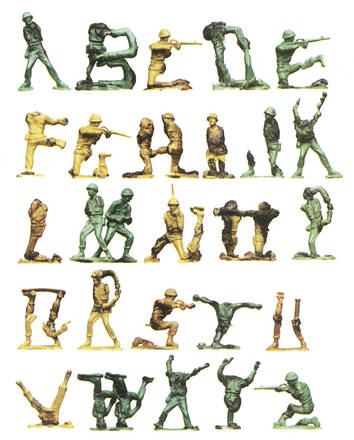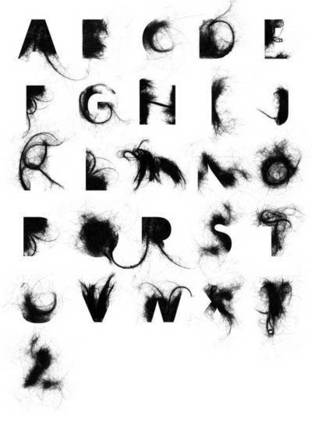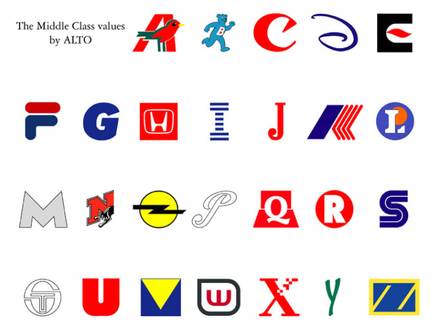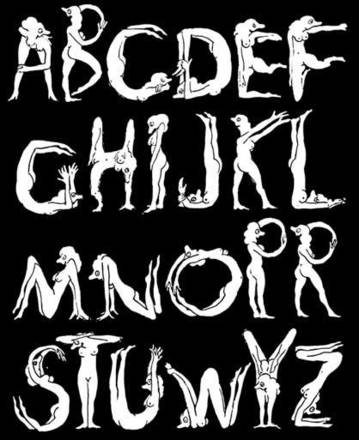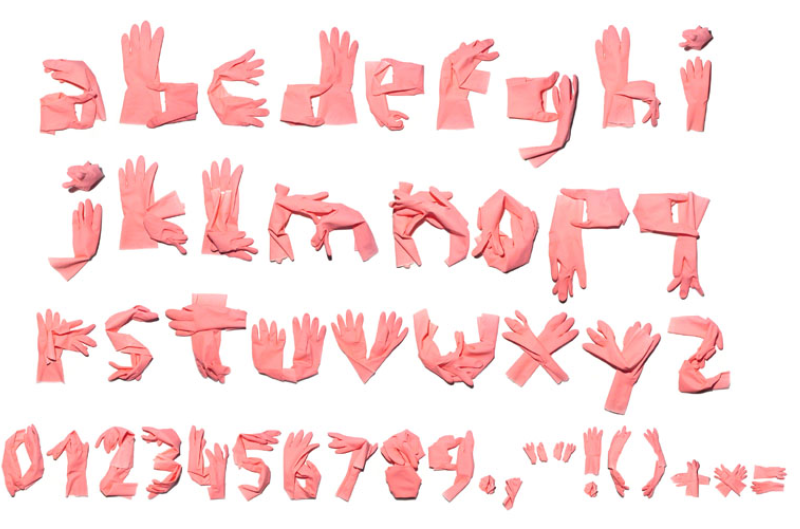
Vajgl font a další „blbnutí“ s písmem
Tento "chutný" nápis jsme nafotili v naší redakci jako ukázku a náš příspěvek k článku o experimentech s písmem. Z čeho všeho lze dnes vytvořit font?
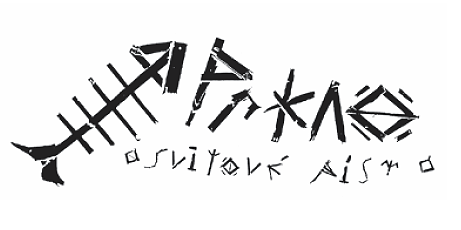
Průkopníkem experimentů s písmem byl u nás asi Petr Babák, jehož písmo Prkno vešlo do dějin (mj. se objeví i v chystané publikaci CI.CZ). Prezentace osvitového písma Prkno byla ve Fontu 11.
Pod vedením prof. Jana Solpery se pak v ateliéru písma na Vysoké škole umělecko-průmyslové podobně experimentovalo i v dalších letech a mnohé z těchto pokusů jsme ukazovali postupně v našem časopise Font.
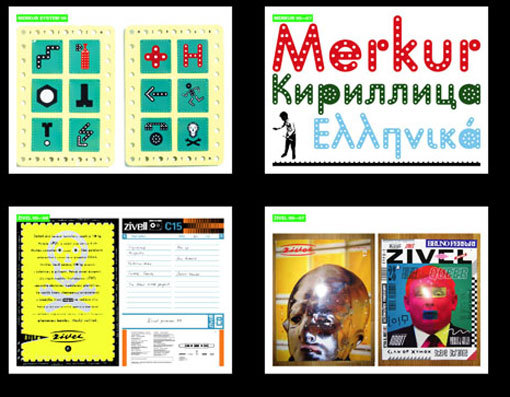
Na častou námitku, že se jedná jen o nesmyslné exhibice bez smyslu a následného využítí těchto „písem“, odpověděl například Marek Pistora využitím svého písma Merkur na některých projektech. (Objevilo se tuším i v Reflexu.) Viz Font 18.
Také ve světě se podobně „blbne“. Ukázka písma z plastových vojáčků je z roku 2006.
Ukázka chlupatého písma Futura. Zdroj: http://www.resetblog.com/index.php/futura-on-the-behance-network/
Objevily se již i fonty sestavené z gumových rukavic, dámského ochlupení, písmenek z polévky, z prstů a dalších končetin... Lidská fantazie nezná mezí. :-)
Písmo pro milovníky logotypů. Poznáte z jakých značek pochází jednotlivá písmena?